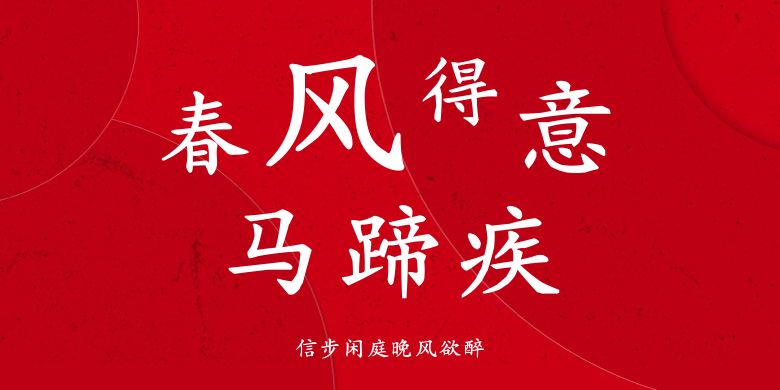
信步闲庭晚风欲醉,这款字体结构工整、笔画清晰,兼顾美观与易读性,适用于标题、正文、海报、包装、LOGO 等多种场景。字形优雅稳定,风格百搭耐看,适配日常排版与创意设计,让文字呈现更舒适、更具质感。信步闲庭晚风欲醉一笔一画,皆是细节,以均衡的比例、流畅的线条打造舒适视觉体验,字形端正大气,风格简约现代。无论是商业设计、品牌宣传还是日常排版,都能轻松驾驭,让文字更有格调与力量。信步闲庭晚风欲醉字体下载。